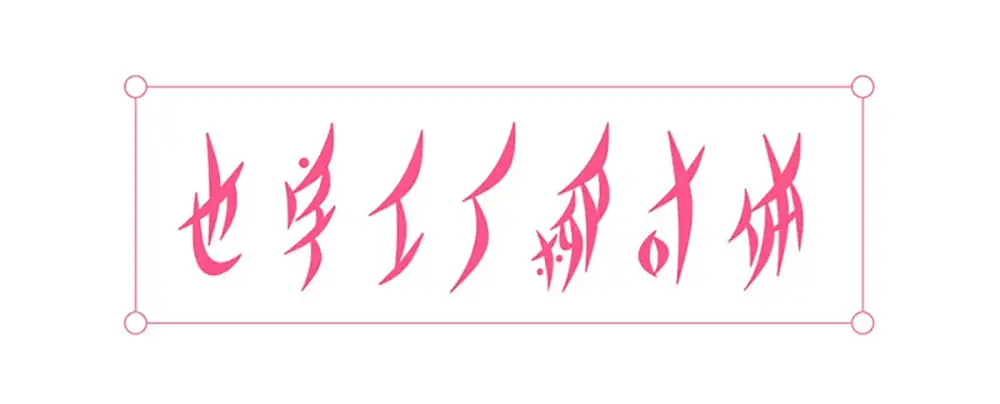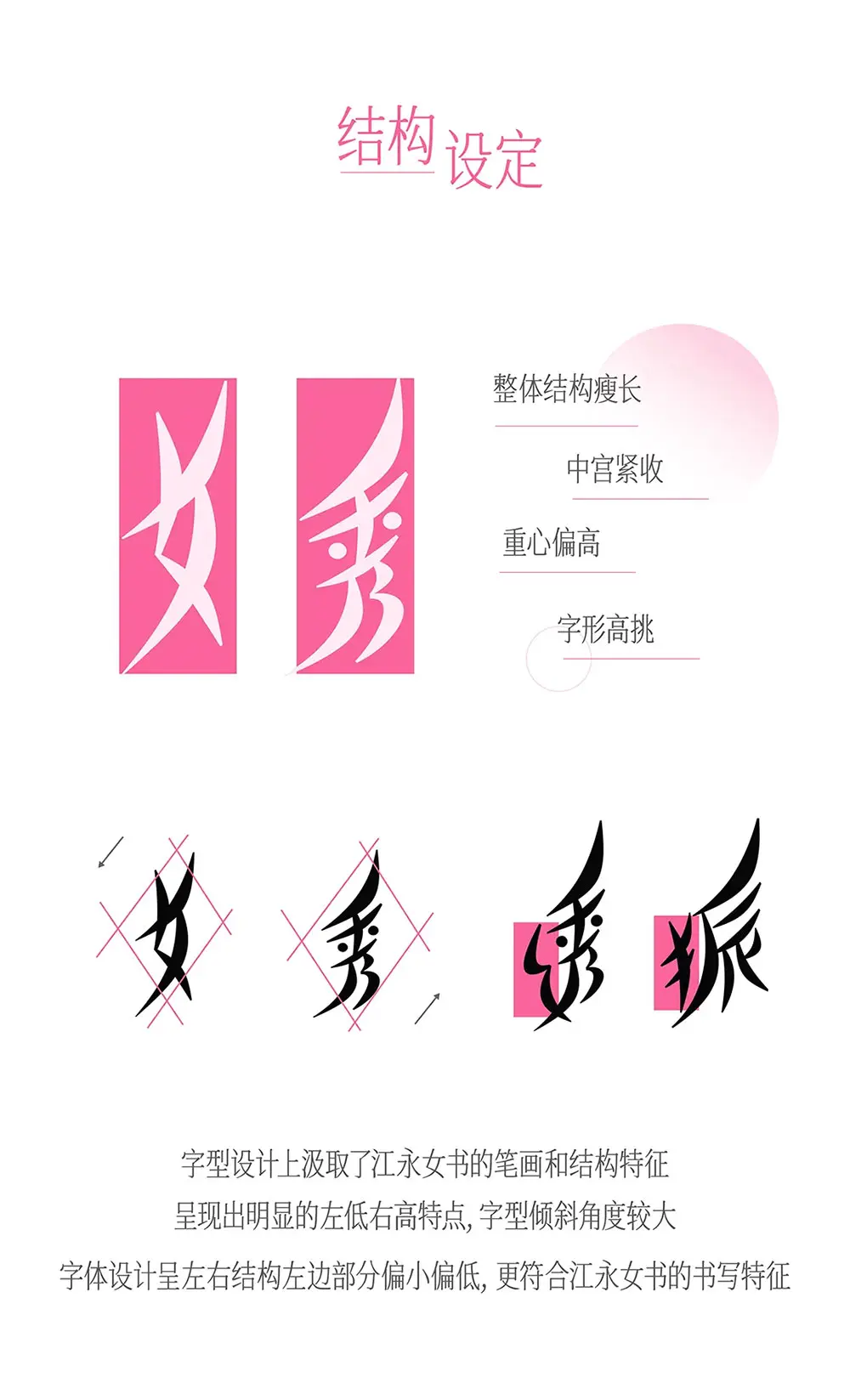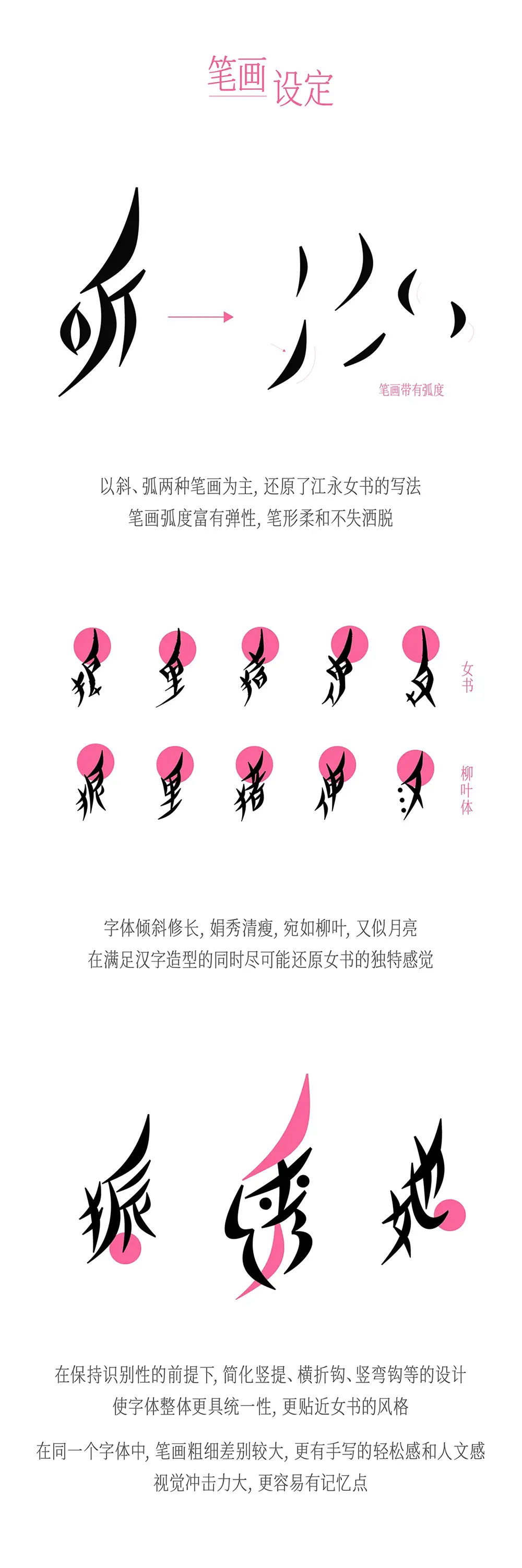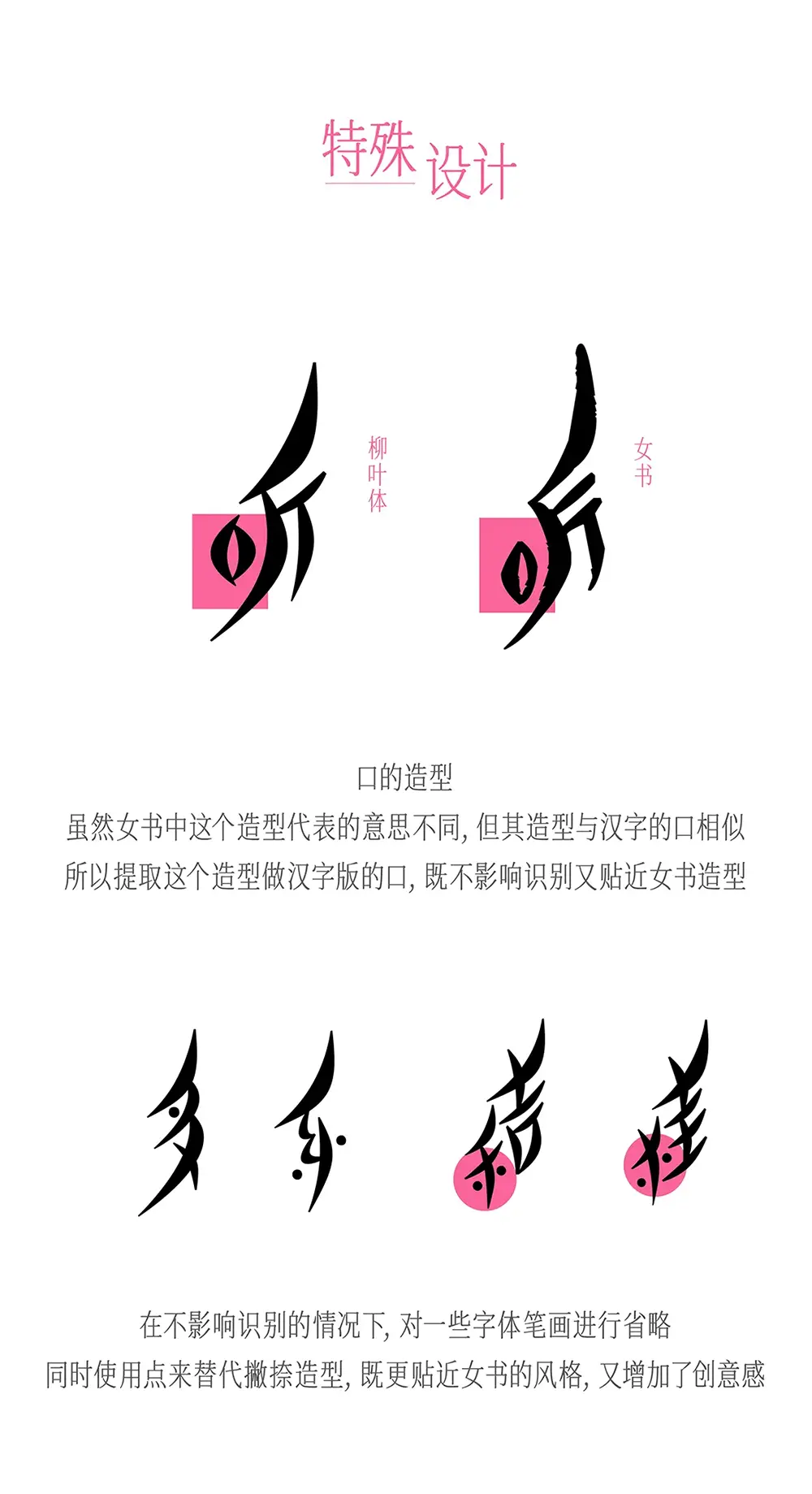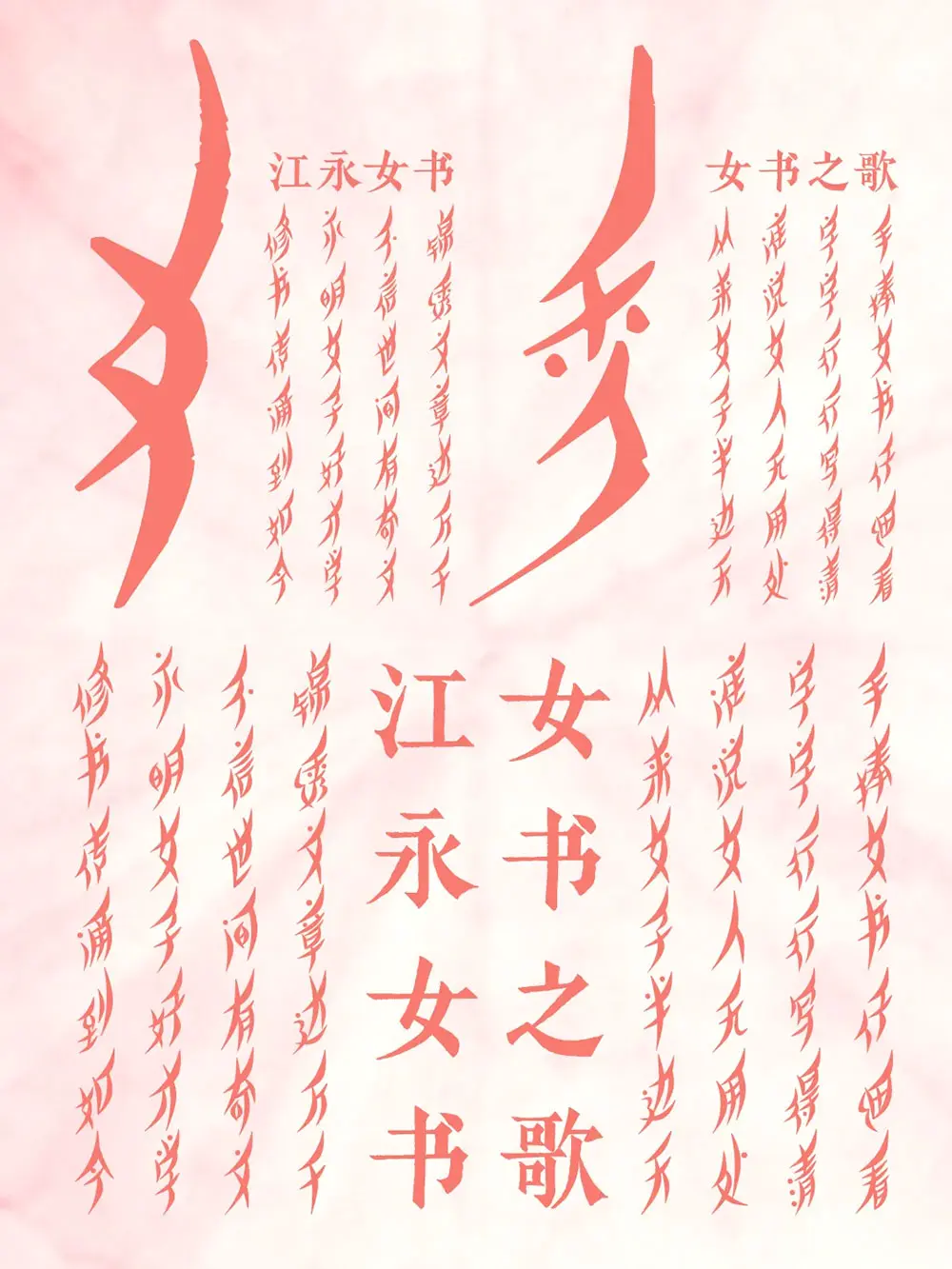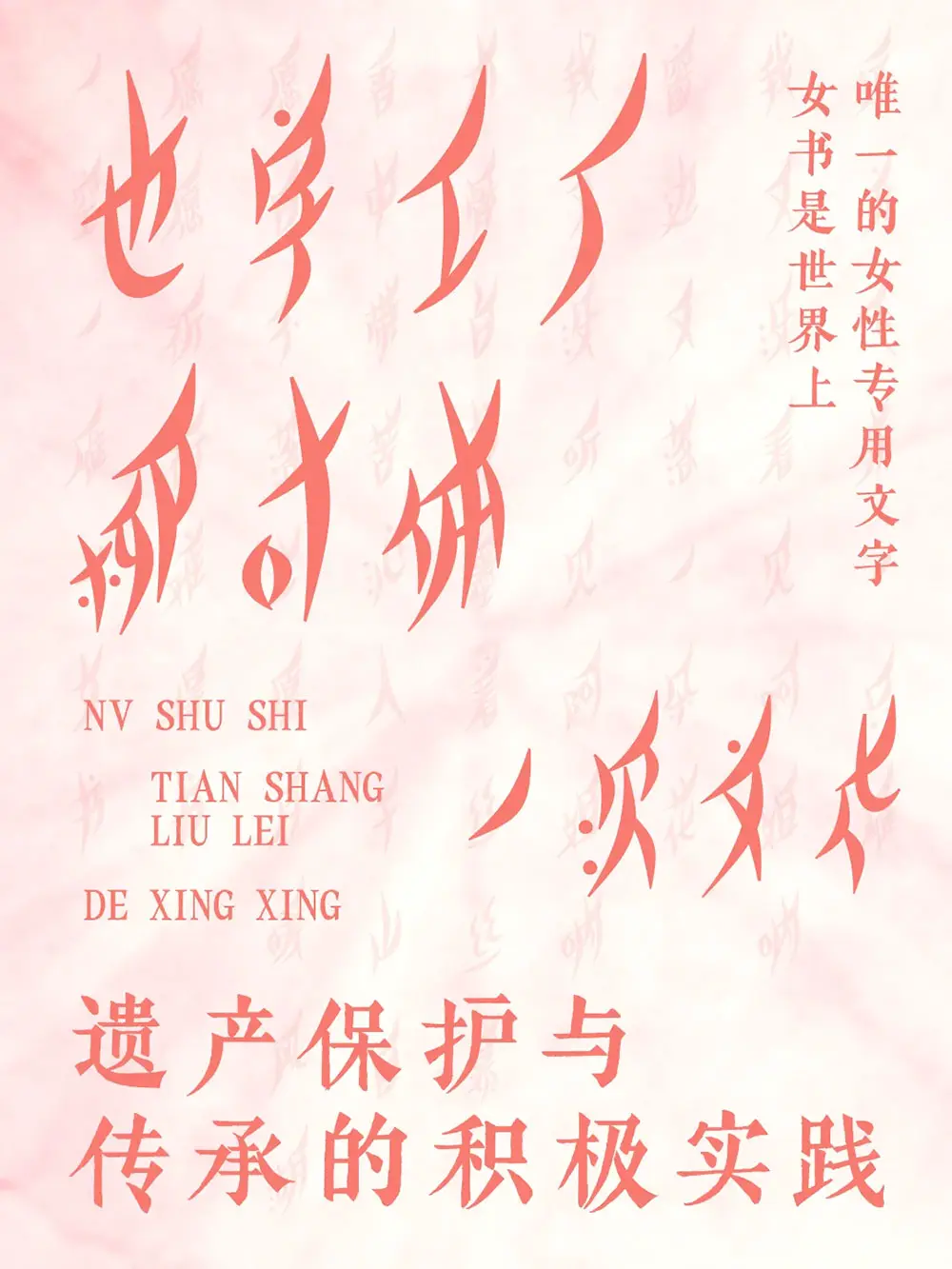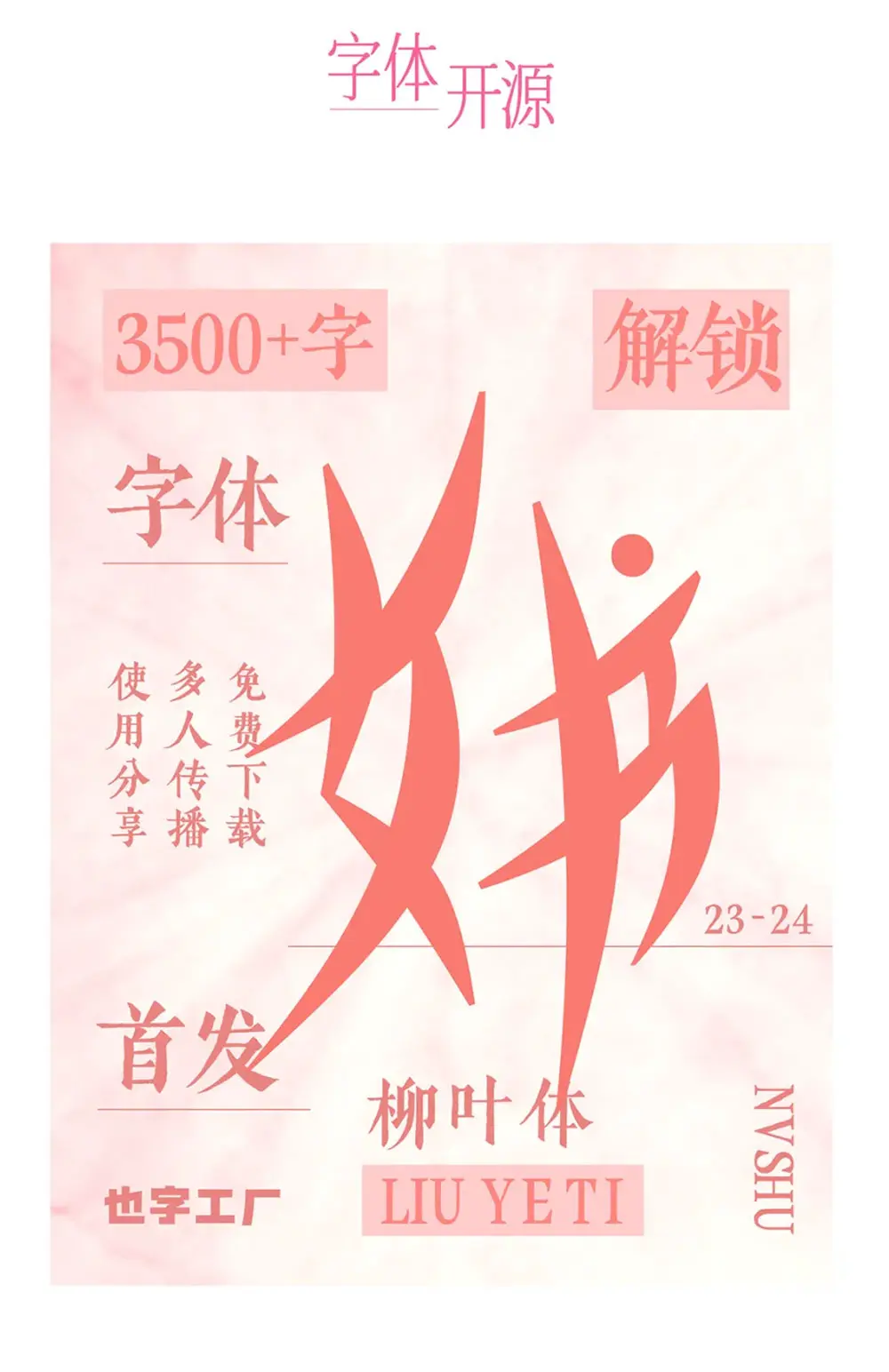
在湖南永州市江永縣東北瀟水流域,當地存在著“一語二文”的現象,在同一片土地上,男人和女人說著同樣的語言卻寫著兩種文字,男人寫端莊的方塊漢字,女人寫秀美的斜體女書。
當文字成為男性的獨有品,女性將如何在史書上證明自己曾經來過?
舊制度的背景下,在以父權為主導的封建禮教的規訓過程中,女性,特別是民間普通勞動婦女被剝奪了學習文化知識的權力,但是江永的女性創造了屬於自己的文字和書寫方式,她們用小木棍、竹篾、蘸上鍋底灰,在紙書、扇面、手帕上面,寫下了婚姻家庭、社會交往、鄉里逸聞、歌謠謎語等內容來表達自己的生活狀態和情感需求,在小小的角落,一顆寄託了女性思想解放的種子逐漸發芽。
作為同村女性之間秘密的通訊方式,女書的流傳多靠母傳女、老傳少的方式,在江永及鄰近的漢族和瑤族婦女間世代傳襲,並且在主人去世後多作為殉葬品焚燒或掩埋,即“人死書亡”,只有寥寥少數作為紀念品珍藏保留。
在2023年,一次偶然的機會讓我們認識了女書文字作為世界上唯一的女性文字,女書成為了中國語言生活中的一個獨特現象,它象徵著一種“陽光文化”,賦予了女性話語權,同時也是一種文化抗爭,猶如一縷陽光為女性生活帶來愉悅。
也字工廠柳葉體,借封建制度下被受壓迫的女性喚醒人們對權益的維護與關注。